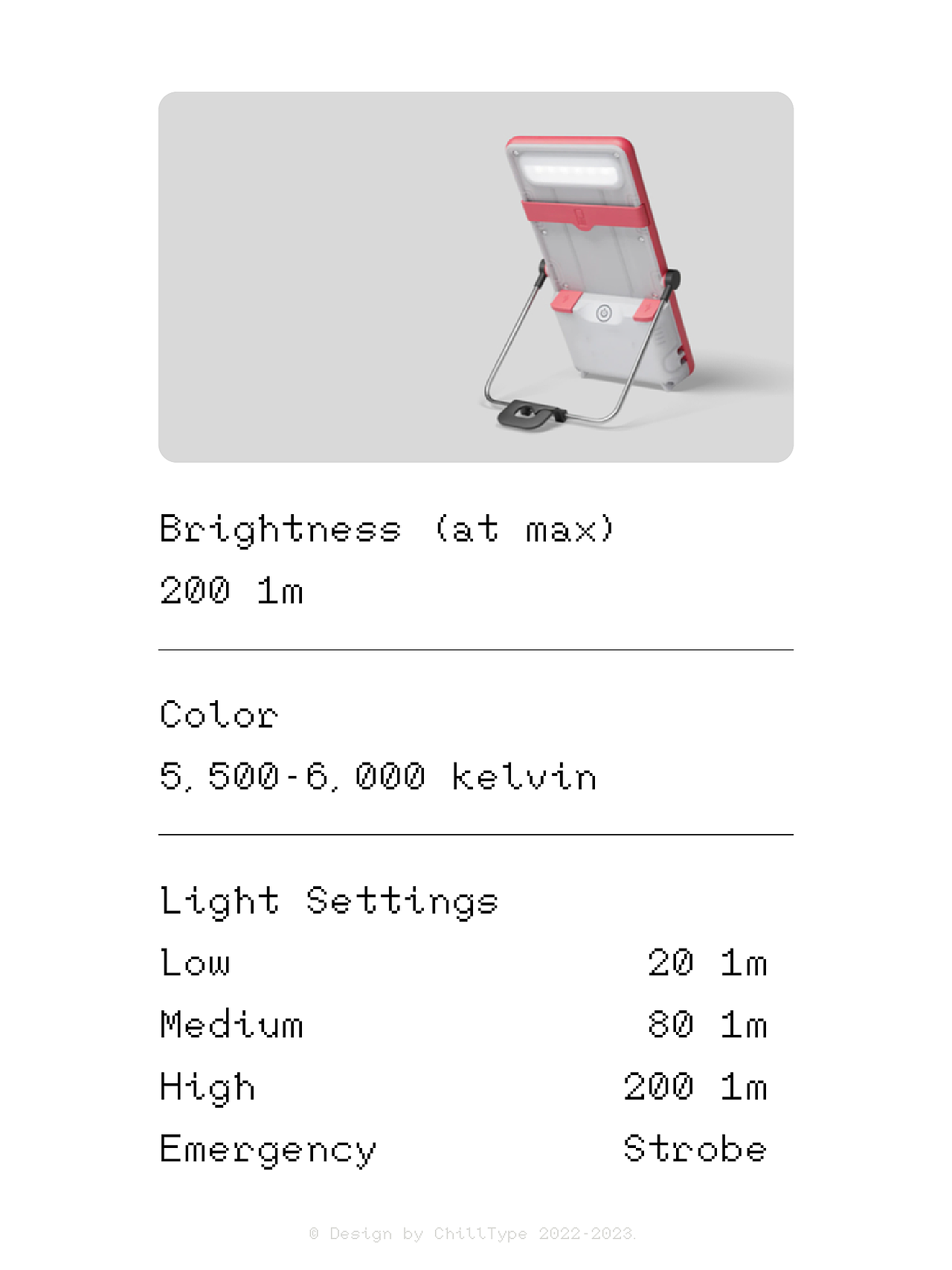
ChillMoon mono(免费商用)
🌕原创等宽像素字体 ChillMoonmono
原创等宽像素字体ChillMoonmono,更具有手写感的人文像素字体,灵感来自于手写字体的笔画,风格独特。
适用于复古潮流的设计,暂不适用于用来敲代码,因为其对识别有一定要求,而此字体更多是保留书写的笔画,保留等宽,并没有对字体整齐度做细致的视觉设计。